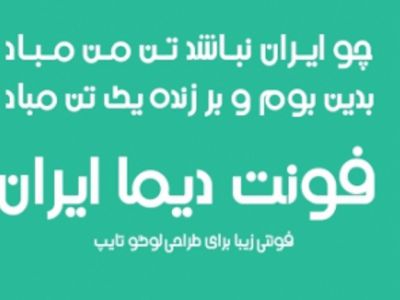
دیما بادیه
این فونت یک فونت عربی است که کاراکترهای فارسی را نیز داراست و برای فارسی نیز میشود استفاده کرد.این فونت توسط طراح سوری در سال 2003 طراحی شده است .Designer in Aleppo, Syria, who made these fonts for Arabic: A-Badie-Shahba (1990, Agfa), Joude, ABH-Ogaret-Light, Badie-Dimah-Normal, Badie-Falcon, Badiefont-Dima, Badiefont-Sabeel, SAHBA-NEW. All were done between 1993 and 2003.
این فونت بسیار زیبا جا برای کار در تایپوگرافی و طراحی لوگوتایپ بسیار دارد.
قلم زیبای دیما بادیه منتشر شده است.